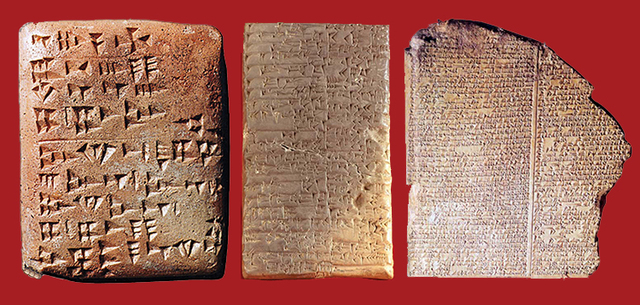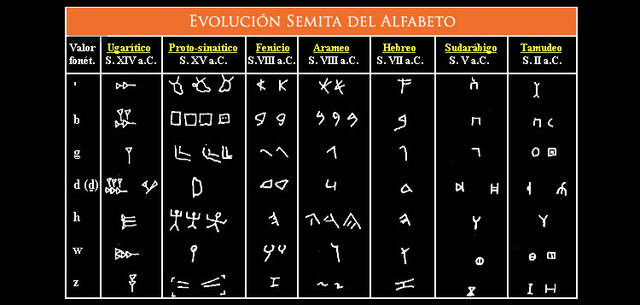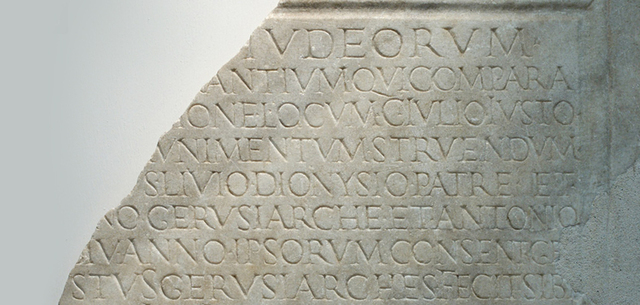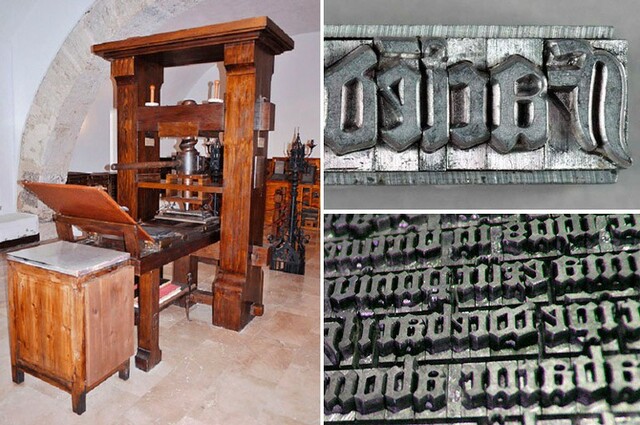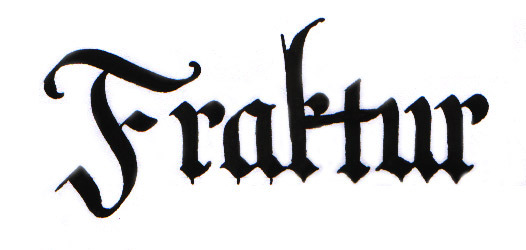
La escritura cuneiforme es conocida como la expresión más temprana de escritura de la cual se han encontrado restos. Se conoce así por el método con el cual se realizaba, utilizando cuñas sobre tablillas. Esta escritura se fue esparciendo y llegó a ser usada en Mesopotamia duran más de 3000 años.
Los primeros en escribir consonantes aisladas fueron los fenicios y los hebreos. Aparece como una combinación de los símbolos de la escritura cuneiforme y los jeroglíficos egipcios. Estos alfabetos contaban con 22 consonantes.
El alfabeto Griego adquiere una gran inspiración en el fenicio y los semitas, pues copia gran parte de los símbolos agregando aquellos con los que representar a las vocales, de esta forma de evitaba el problema de no tener un símbolo que representara a las vocales como en los fenicios. Este alfabeto se extendió por el mundo y dió origen a otras lenguas e idiomas.
El alfabeto Romano es el más utilizado hoy en día. Fue adoptado por los romanos de los etruscos, los cuales a su vez tomaron el suyo de la propios griegos. Este alfabeto, también conocido como alfabeto latino, contaba sólo con 21 letras, además de que no existían minúsculas en si mismas, las nuevas representaciones datan de finales de siglo.
Antes de la imprenta que todos conocemos, existieron ya algunos intentos para imprimir y poder realizar escritos a una mayor escala, como los romanos que contaban con sellos que imprimían en objetos de arcilla. En China, durante los años 1041 y 1045 fue creada un primer intento de imprenta, lo cual era descrito como un sistema de tipo móvil el cual permitía el pintar en porcelana todos los caracteres de la escritura china, por lo que está no resultaba en una tarea sencilla.
Con la llegada de la imprenta, la tipografía pasó a ser muy valorada, formando parte de la alta sociedad , que era ilustrada y con ganas de conocimiento. Habiendo una gran transición entre las tipografías góticas y las que fueron surgiendo, con la llegada de los libros a las personas de clase alta, el conocimiento fue expandiéndose y muchas más personas recibieron educación. Un ejemplo de tipografía puede verse en "fraktur*.
La primera obra que se reprodujo fue el "Misal de Constanza", aunque se pone en duda la verdadera fecha de procedencia de está impresión, por lo que la Biblia de 42 líneas es la primera y la más importante obra impresa. Con el tiempo y debido a la crisis Gutenberg se vió obligado a compartir su invento a otras imprentas para subsistir
Johann Gutenberg revolucionó la imprenta al crear un sistema que permitía una casi automatización completa del proceso de escritura e impresión de los libros. Su trabajo de herrero y manejo del oro fue lo que junto a su asociación con Johann Fust le permitió crear este revolucionario invento..
A este periodo se le conoce de transición, porque si bien es cierto que mucha de la tipografía ya existente era mejorada, este servía más como un periodo de preparación entre esto y el clasicismo. El barroco era conocido también porque iba a la inversa del renacimiento,llevando las obras al extremo con composiciones complicadas y arquitecturas colosales.
En este periodo ocurre mucho del refinamiento de la tecnología usada para reproducir la tipografía. Este movimiento se inspira en la Grecia Clásica. Tipograficamente hablando, los trazos gruesos se agudizan y las formas de estos están más estilizadas. Surgen como resultado las romanas modernas Didot y Bodoni. Claro que algunas de estas perdían legibilidad, pero eran por mucho más elegantes.
Esta máquina era conocida como una de las primeras máquinas de escribir, si bien en su concepto no lo fue, debido a que se describía solo como un intento primitivo de crear una máquina de escritura además que en manos del propio inventor está resultaba más lenta que escribir a mano. Fue desarrollada por William Austin Burt.
Después de muchos intentos de patentes de máquinas de escribir en América y Europa, se sabe que la primera máquina de escribir que tuvo un relax éxito comercial fue la de Christopher Sholes, que tiempo después logró ser comercializada por la familia Remington, manteniendo su diseño y siendo un éxito ante los demás modelos, conservando así su estructura base: teclas que al ser presionadas suficientemente fuerte podían hacer que el carácter que se buscaba fuera impreso.
Las máquinas de escribir se tornaron tan populares que con el paso del tiempo fueron parte de la vida normal de muchas personas, llegando incluso a ser mejoradas en distintos momentos, como al agregar color mediante un mecanismo, lo cual ayudaba en su momento a la contabilidad, pues ciertos valores negativos debían de estar en rojo para ser representados.
Con la llegada del internet y las primeras computadoras, las máquinas de escribir fueron reemplazadas totalmente y con esto la tipografía se vió beneficiada puesto que la reproducción de está podría ser comparada con un proceso automático y la personalización de nuevas y distintas fuentes, lo que a su vez fue clave en desarrollo de la publicidad. Actualmente a tecnología y la tipografía trabajan en conjunto, permitiendo así un mensaje mejor transmitido con estilos mucho más adecuados al público